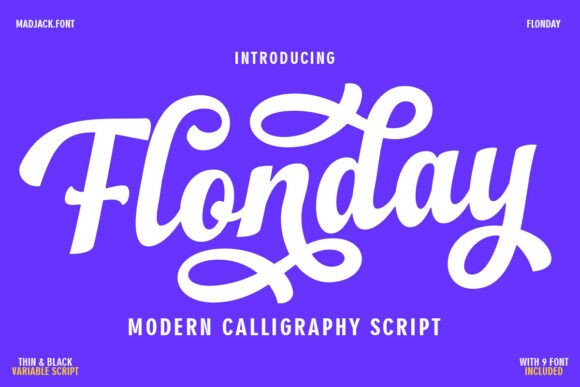
Flondayscript Regular
Nếu bạn đang tìm kiếm các tài nguyên chất lượng cao như Flondayscript Regular, gói cao cấp này là một lựa chọn tuyệt vời cho các dự án sáng tạo của bạn.
Cho dù bạn đang tạo sản phẩm POD (In theo yêu cầu), thiệp mời đám cưới hay đồ họa mạng xã hội, Flondayscript Regular đều là một sự lựa chọn lý tưởng.